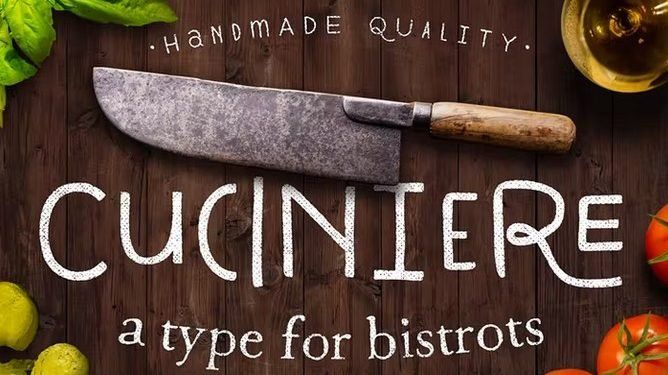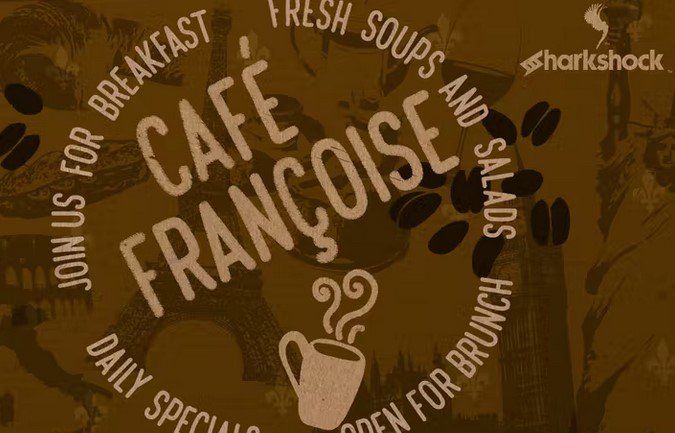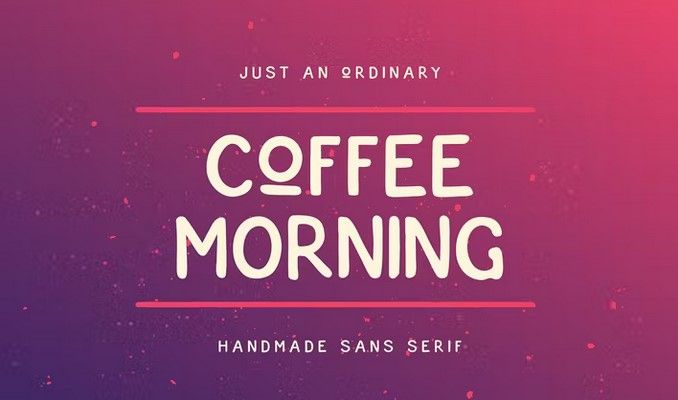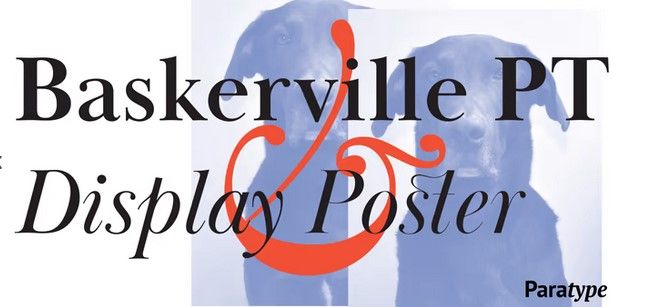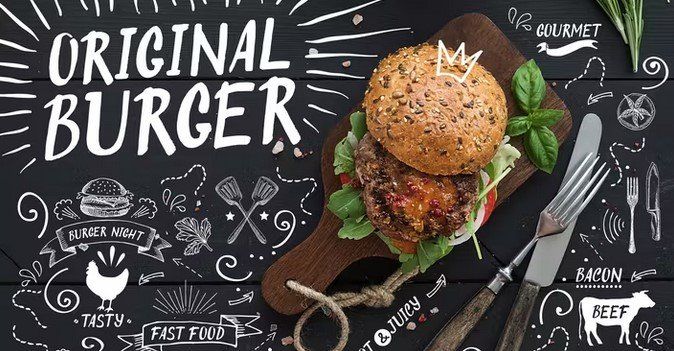
レストランの16メニューフォントの選択
レストラン経営者は、数日、数週間、数か月、さらには一生をかけて、飲食店に最適なメニューを開発する場合があります。 メニューのデザインがあまりにも多く残っていて、常連客が中にリストされている高品質の料理に興味がないのであれば、それは残念です。 メニューは多くの場合、レストランに対する顧客の第一印象を表しており、ユニークで読みやすく、魅力的なフォントでデザインされていることが重要です。
あなたのレストランにぴったりのメニューフォントを選ぶ方法
AdobeFontsやEnvatoElementsなどの最高のフォントサイトから何百万もの書体を選択できますが、レストランに最適なメニューフォントをどのように選択しますか?
最高のメニューフォントを選択するために、プロのデザイナーである必要はありません。 メニューを最初から作成する場合でも、レストランのメニューメーカーに依存する場合でも、次のヒントを考慮して、レッティングの完璧な組み合わせを選択してください。
フォントファミリーを特定する
メニューデザインにプレミアムフォントを選択する前に、レストランのブランドを最もよく表すフォントファミリを決定することにより、オプションを大幅に絞り込むことができます。 サンセリフまたはセリフ書体を含むフォントを選択しますか? おそらく、手書きのスクリプトフォントや斬新な表示タイプを好むかもしれません。
明瞭さと読みやすさに焦点を当てる
レストランの常連客は、メニューを読むために目を凝らしたくないので、視力の弱い顧客でも読みやすくクリアなメニューフォントを選択するようにしてください。 メニューが読めないと、新しい食べ物を試す常連客にはなれないでしょう。 レストランのメニューデザインにユニークで印象的な書体を選びたい場合は、明快さを犠牲にしないように注意してください。
メニューのトーンを決定する
あなたのレストランのメニューにどのような気分を刺激してもらいたいですか? フォントは、ブランドが提示する全体的なトーンを決定する上で大きな重みを持ちます。 あなたのレストランをクラシックでエレガントなものとして知られたいですか? セリフ書体を選択してください。 楽しくて冒険的ですか? サンセリフまたはいくつかの手書きフォントを使用してください。 選択したメニューフォントはブランドに個性を与え、間違った書体を選択すると混乱する食事体験につながる可能性があります。
あなたのブランドを強化する
あなたのレストランには独自のロゴがありますか? メニューフォントを選択するときは、ブランドの既存のデザインを考慮してください。 フォントを正確に一致させることができない場合は、サイン、ロゴ、またはその他の食品包装やディスプレイと同じフォントファミリのタイプフェイスを選択することを検討してください。 たとえば、ロゴが繊細なスクリプトフォントに依存している場合、メニューデザインにリラックスしたサンセリフ表示フォントを使用するのは最善の方法ではない可能性があります。
レストランのための最高の手書きメニューフォント
手書きフォントは、本物の人間の書き物に似せて設計された書体であり、顧客とブランドの間の個人的なつながりを促進するため、メニューフォントとして人気があります。 手書きフォントは、注目に値する印象的なメニューデザインにもなります。 メニューに最適な手書きフォントは何ですか?
1.ティンバーライン
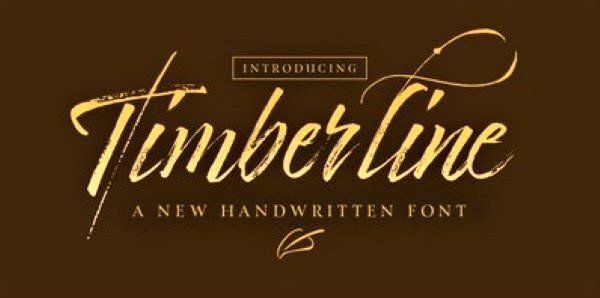
Adobe Fontsやその他の人気のあるソースから入手できるTimberlineフォントの優雅なストロークと質感のあるラインは、レストランのメニューに個性を与えることを約束します。 用途の広いフォントは、おしゃれでトレンディなコーヒーショップから、クラシックでエレガントな高級レストランまで、さまざまなレストランのメニューを際立たせることができます。
2.失礼なクッキー
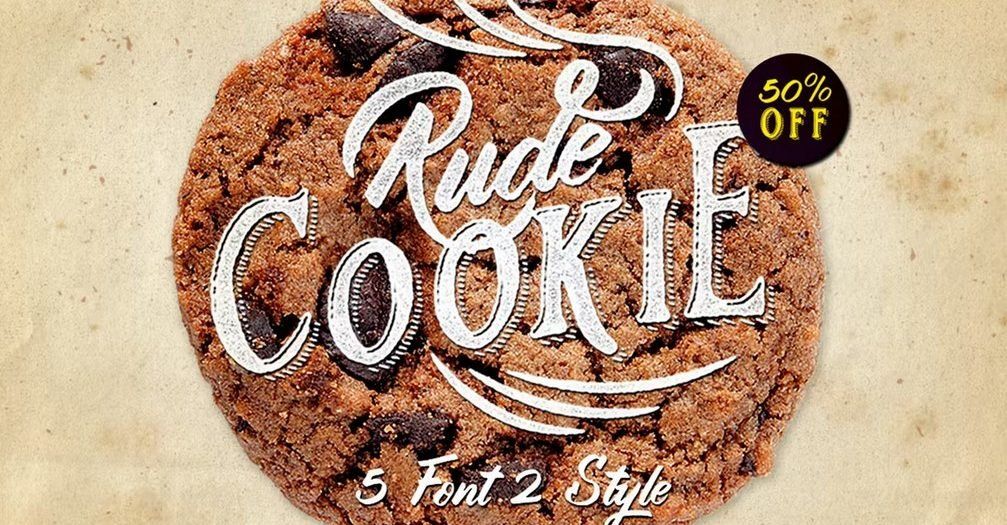
真のキャラクターを備えたユニークな手書きフォントであるRudeCookieフォントは、レストランのメニューで際立っており、お客様を喜んで施設に迎えることを約束します。 Rude Cookieは、EnvatoElementsを含むさまざまな人気のあるソースから入手できます。
3.急いで
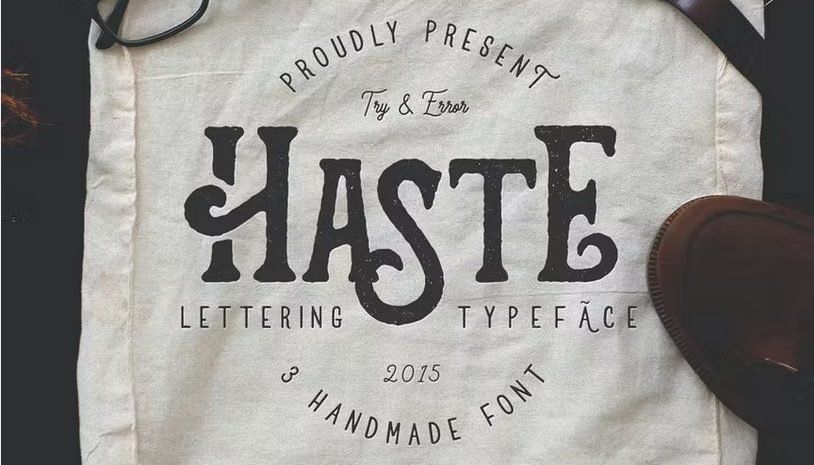
レストランのメニューデザインで人気のあるもう1つの手作りフォントであるHasteフォントは、他のオンラインソースの中でも特にEnvatoElementsから入手できます。 手書きのアートに本当に似ているそのユニークなキャラクターのおかげで、ヘイストはそれが飾るメニューのハイライトになるはずです。
レストランに最適な表示フォント
メニューのタイトルや見出しに最適なディスプレイフォントは、より大きなサイズで表示するために特別に設計されたタイポグラフィです。 外観が拡張されているため、ディスプレイフォントは、他のフォントよりもクリエイティブな要素を使用してデザインできることがよくあります。 レストランのメニューデザインに最適な表示フォントは何ですか?
4.アルマディラ
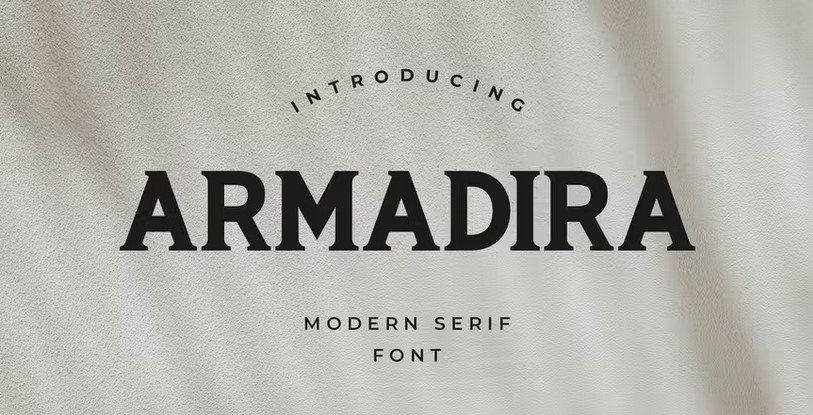
Armadiraディスプレイフォントの明瞭さは、意図したメッセージを明確に伝えることを約束します。 Envato Elementsやその他の人気のあるフォントサイトから入手できるArmadiraフォントは、レストランのメニューデザインの内容を示す時代を超越したクラシックになるはずです。
5.デコヘッド
Decoheadは、さまざまな幅の優雅なストロークが特徴のエレガントな表示フォントです。 アールデコ調の書体は、Envato Elementsやその他の人気のあるフォントサイトから入手でき、メニューデザインに洗練されたトーンを加えることを約束します。
6.モーサーン
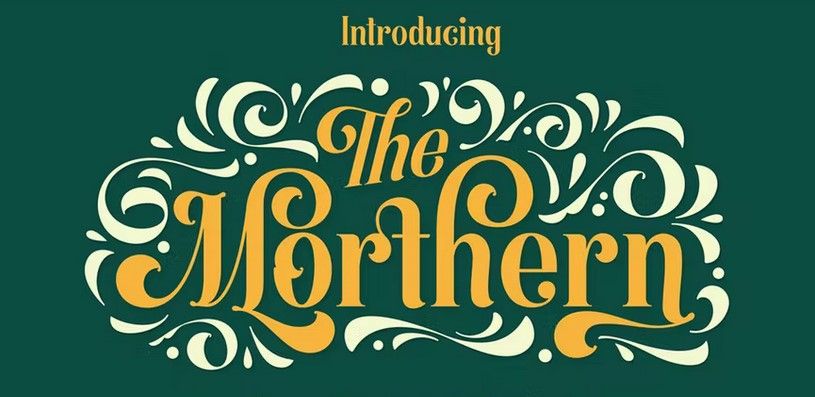
あなたのレストランの魅力と奇抜さを反映したメニューフォントを選びたいですか? Morthernフォントは、オールドスタイルの文字を使用した活気のある表示フォントであり、EnvatoElementsやその他の人気のあるソースで見つけることができます。
Resturauntメニューに最適なサンセリフフォント
サンセリフ書体は、クラシックなスタイルと読みやすさから、最高のレストランメニューフォントのいくつかになります。 基本的なサンセリフは、最も人気のあるメニューフォントの一部です。そのシンプルさにより、実質的にあらゆるデザインと組み合わせることができ、その明快さにより、レストランの常連客が文字を読みやすくすることができます。
7.クシニエール
Envato Elementsやその他のオンラインソースから入手できるまったく新しい書体であるCuciniereフォントは、食品愛好家のために特別に設計されました。 ユニークなフォントは文字で溢れ、サンセリフ文字の構造を維持しながら、手書きの書体にほぼ似ています。
8.カフェフランソワーズ
シンプルでありながら魅力的な書体は、レストランのメニューのハイライトになるはずです。CafeFrancoiseフォントは、その日のカフェのスペシャルを紹介する屋外のチョークメニューボードの看板から着想を得ています。 フォントは複数のソースから入手できますが、EnvatoElementsで見つけることができます。
9.コーヒーモーニング
手作りのサンセリフフォントであるCoffeeMorningは、その明瞭さと読みやすさを維持しながら、陽気なタイポグラフィでお客様をお迎えします。 Envato Elementsで入手できるフォントは、不完全な形状とラフなストロークが特徴で、多くのレストランで知られることを望んでいるキャラクターになっています。
メニュー項目のよりすばらしいフォント
居心地が良く、パワフルで、思い出に残るレストランメニューのデザインを作りたいですか? 上記のフォントの選択肢に制限しないでください。 メニュー項目には他にも素晴らしいフォントがたくさんあります。
10.バスカヴィルPT
メニューの目的は読むことであるため、メニュー項目の詳細を示すタイポグラフィが明確で読みやすいことが重要です。 他のソースの中でもAdobeFontsから入手できるBaskervillePTフォントは、人気のあるセリフ書体であり、レストランのメニュー項目に最適なフォントです。
11.オリジナルバーガー
ヒップバーガージョイントに最適なオリジナルバーガーフォントは、EnvatoElementsやその他の人気のあるフォントサイトから入手できます。 大文字、句読点、数字で構成される手作りのフォントは、エキサイティングでリラックスできるレストランの雰囲気にふさわしいトーンを設定します。
12.ジャザ
高級ダイニング体験への古典的な追加であるGiazaフォントは、滑らかな曲線を使用して美しいセリフ書体を作成します。 フォントは、EnvatoElementsを含むさまざまな人気のあるフォントサイトから入手できます。
13.セオドア手書き
手書きの書体であるTheodoreHandwrittenフォントは、メニューのハイライトとメニュー項目の詳細の両方に適した最新のスクリプトです。 フォントは、EnvatoElementsやその他のさまざまな最高のフォントサイトから入手できます。
14.ケネイシャ
カリグラフィスクリプトフォントでメニューを強調したいですか? Keneishaフォントは、エレガンスとスタイルを伝えるように設計された、さまざまなベースラインを備えています。 Envato Elementsを含むオンラインソースから入手できるこのフォントは、あらゆるメニューのクリエイティブなデザインを強化することを約束します。
15.ブリオッシュ
モダンでありながらクラシックなセリフフォントであるブリオッシュは、シャープなエッジと滑らかなラインが特徴で、エレガントなレストランやカジュアルな食事に理想的なメニュー書体を作成します。 Envato Elementsが提供するフォントは、多くの文字の代替機能を備えているため、メニューデザインに多目的に使用できます。
16.ライノタイプディドット
明瞭さと読みやすさで知られる人気のセリフフォントであるLinotypeDidotフォントは、AdobeFontsから入手できます。メニュー項目を印刷するための優れた代替手段になります。
メニューに最適なフォントは何ですか?
メニュー項目に最適なフォントは何ですか? レストランメニューに選択したフォントは、顧客があなたの中小企業をどのように認識するかに大きく影響する可能性があります。 最高のメニューフォントはBaskervillePTです。 セリフ書体は、さまざまなサイズで読みやすく、高級感と優雅さを伝えるため、レストランのメニューデザインに最適なフォントです。
メニューに最適なフォントサイズはどれくらいですか?
メニューフォントは、視力が完全ではないダイナーでも読みやすいものにする必要があります。 レストランメニューに最適なフォントサイズは20〜30ポイント以上ですが、見出しとタイトルはより大きなフォントにする必要があります。 表示メニューの場合、テキストは、顧客とメニューの間の距離が10フィートごとに1インチ大きくする必要があります。
メニューの読みやすいフォントとは何ですか?
読みやすいメニューをデザインするために、単純なフォントを選択するのが最善の場合もあります。 レストランメニューの読みやすいフォントをお探しの場合は、Helvetica、Arial、Georgiaなどの基本的なサンセリフフォントをお試しください。 Coffee Morningは、レストランのメニューに独特の特徴を与えるモダンなひねりを加えた、読みやすいサンセリフ書体でもあります。